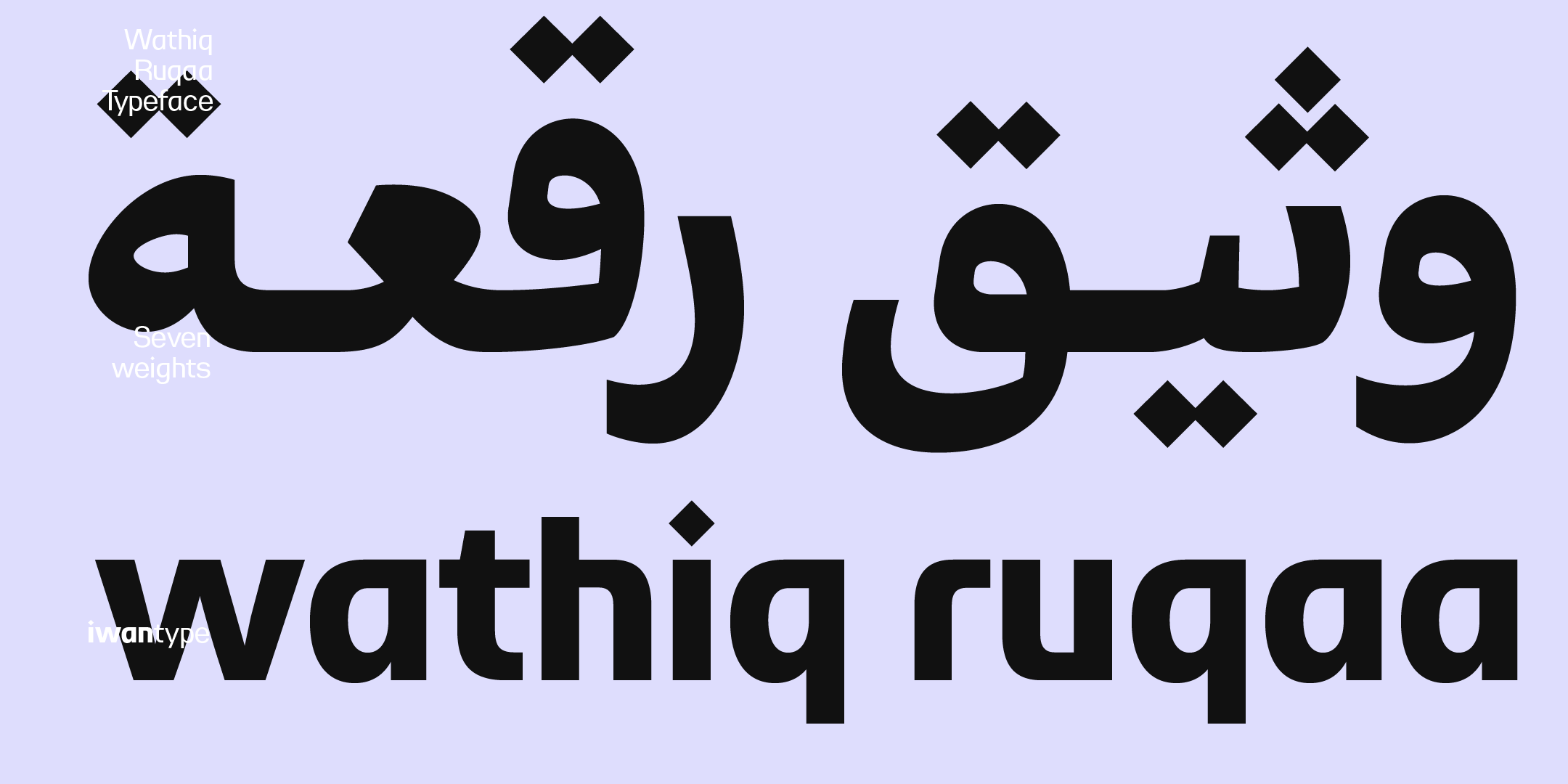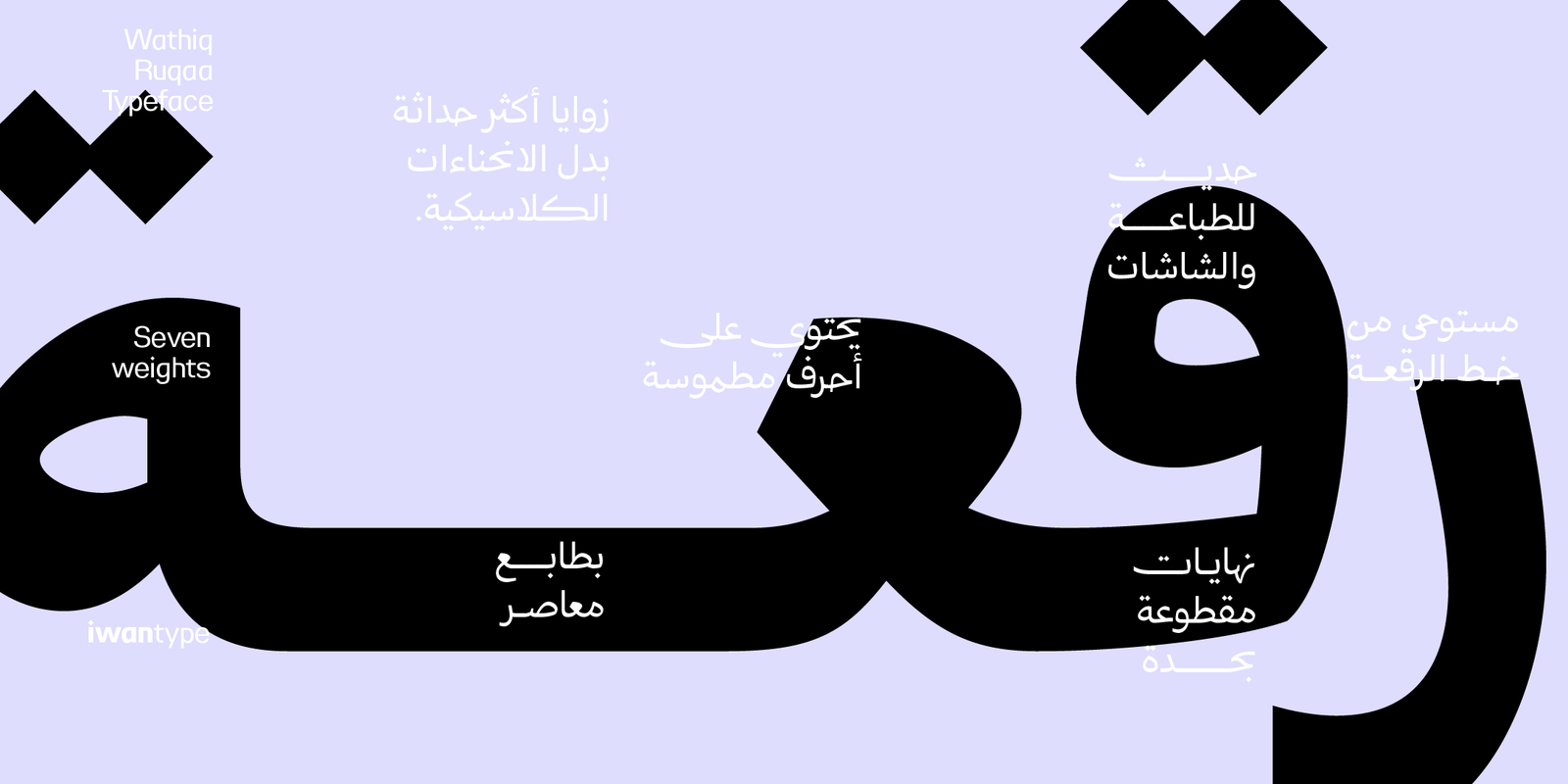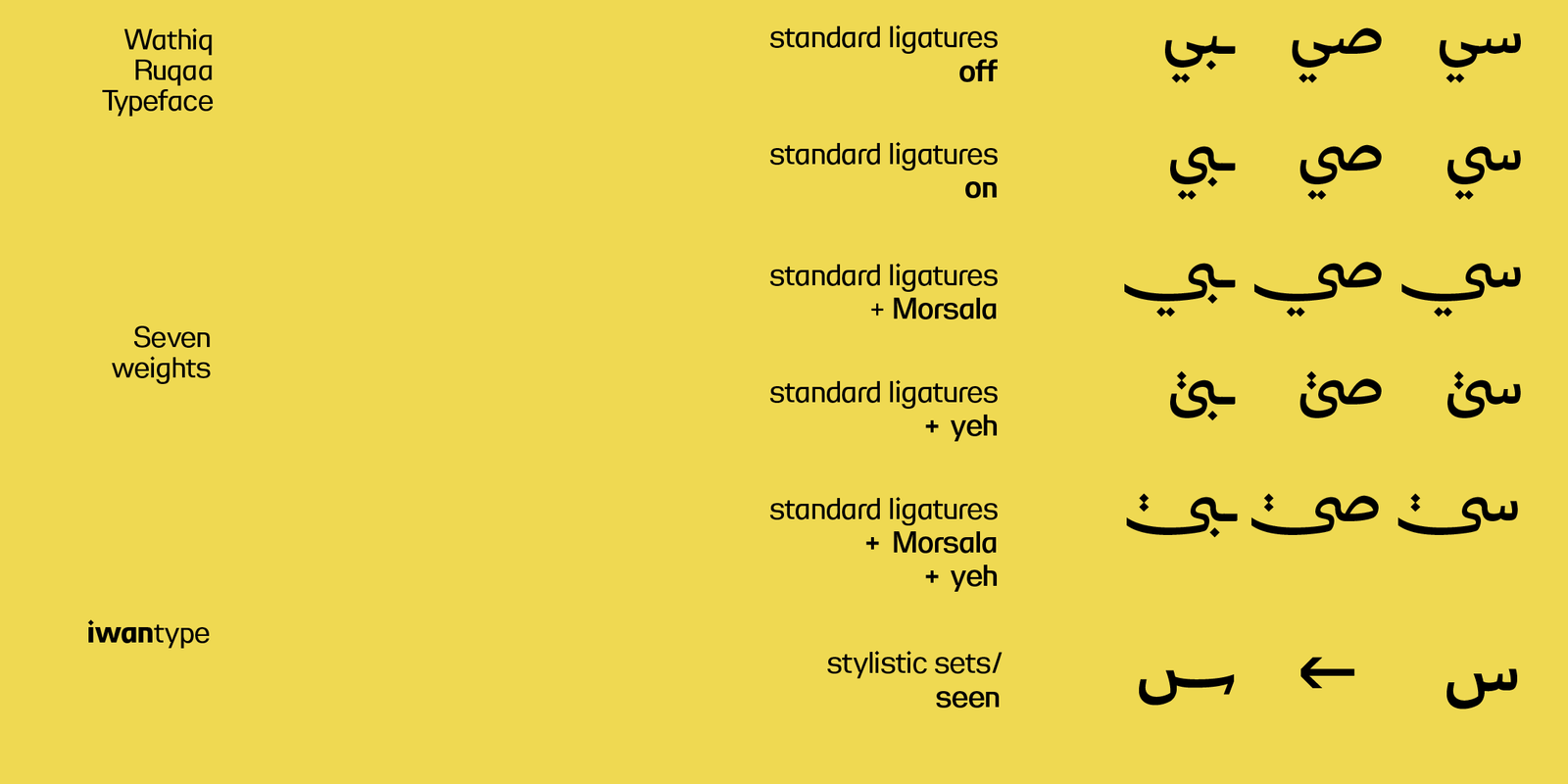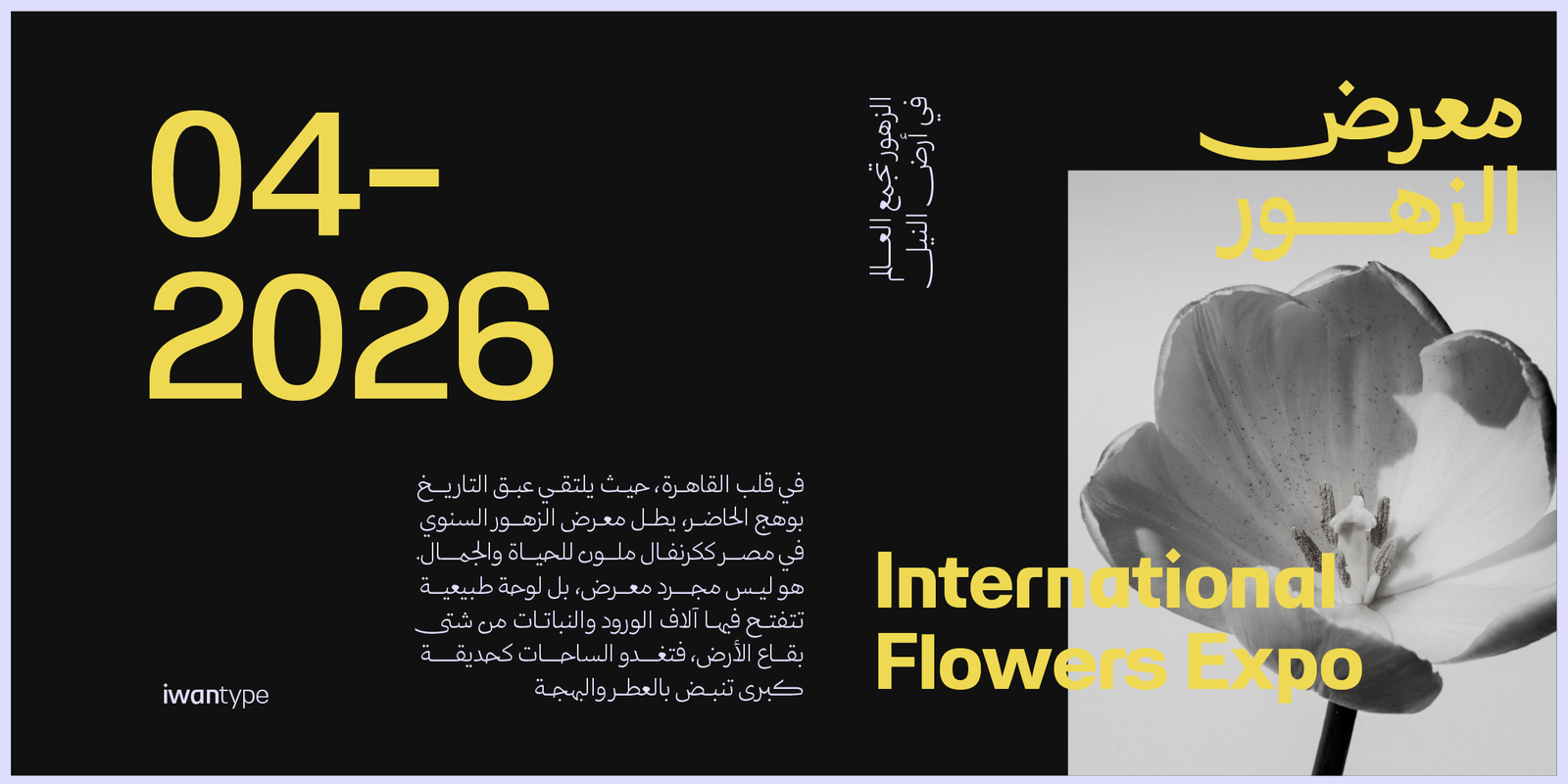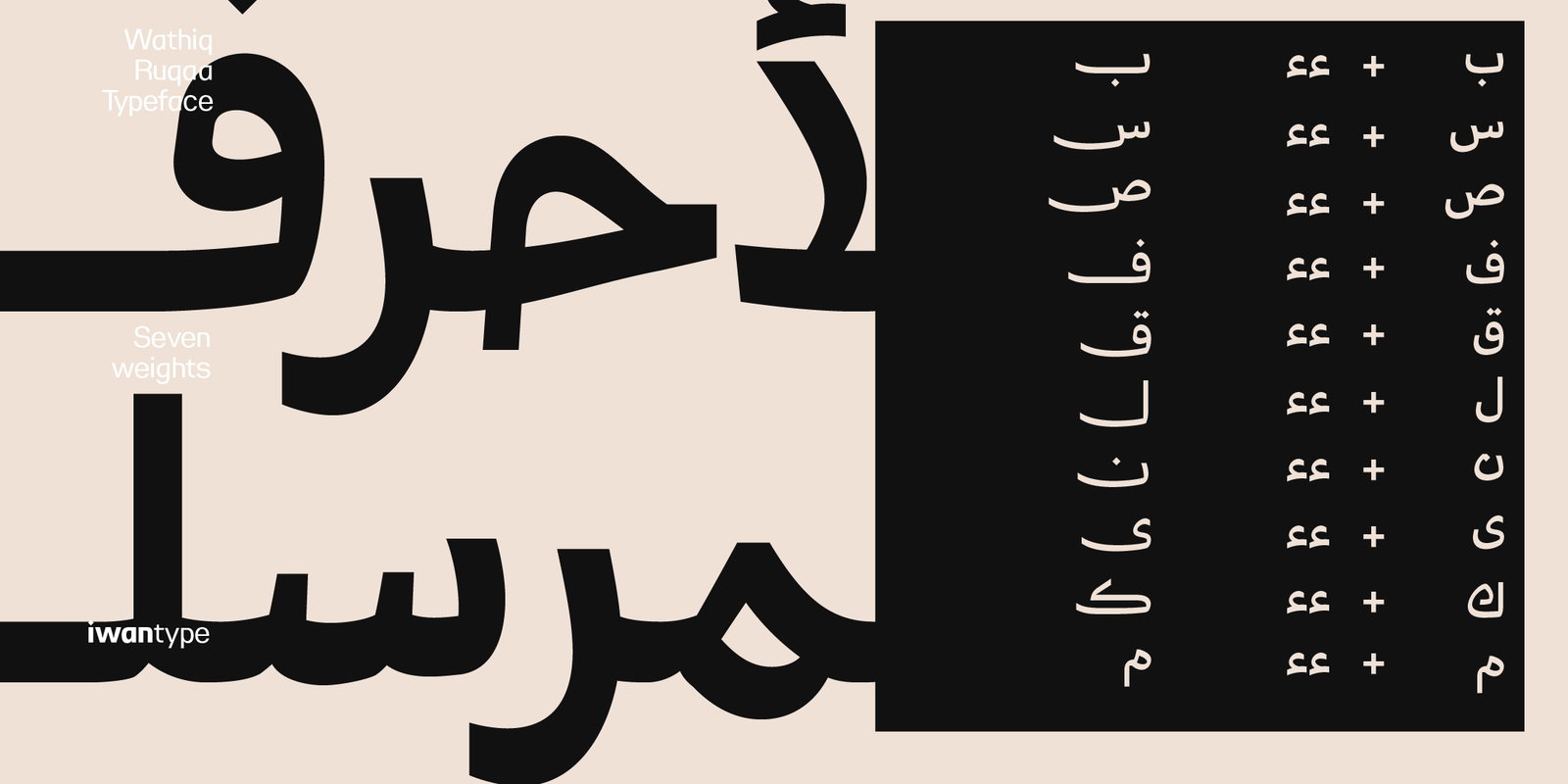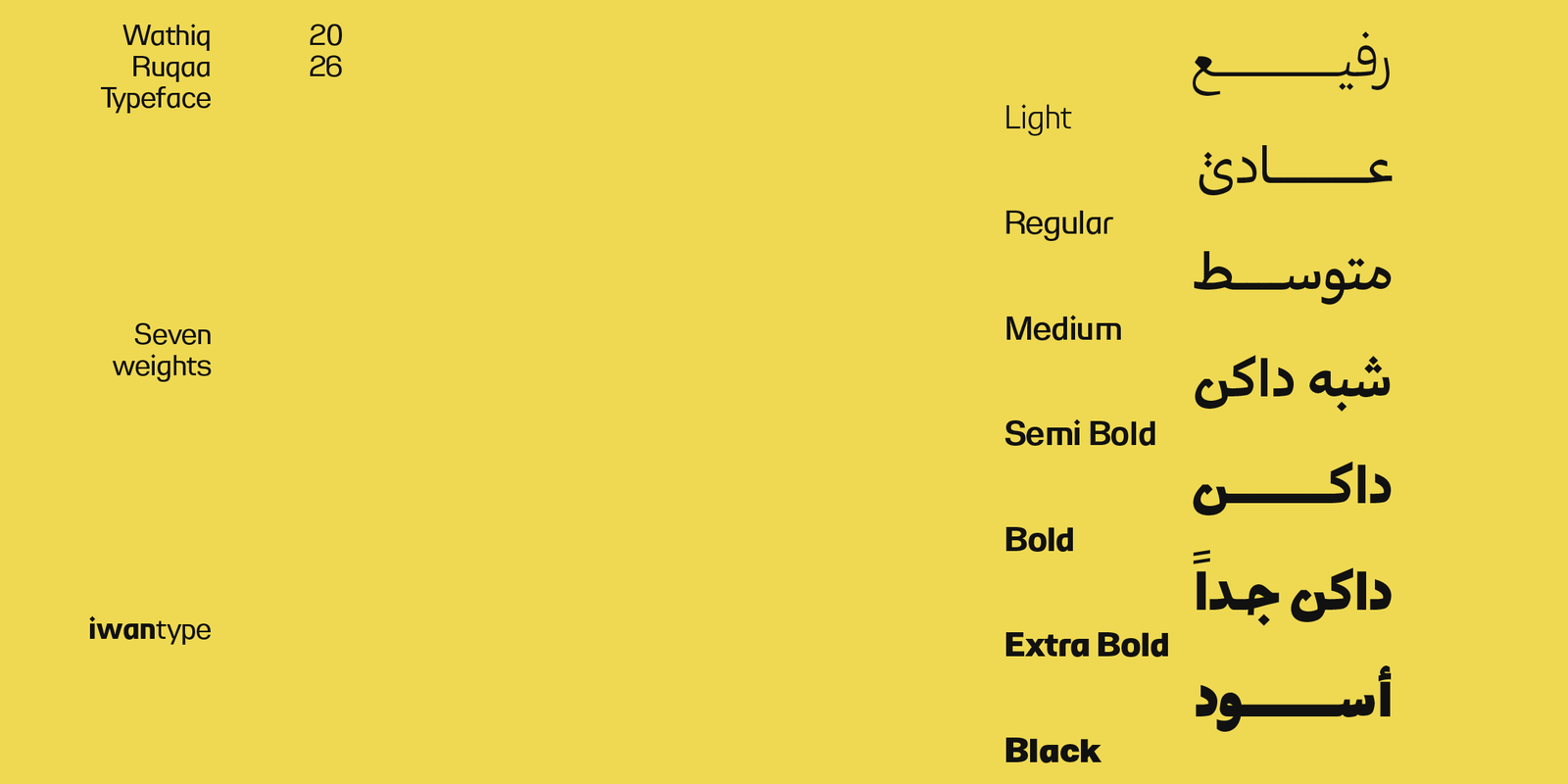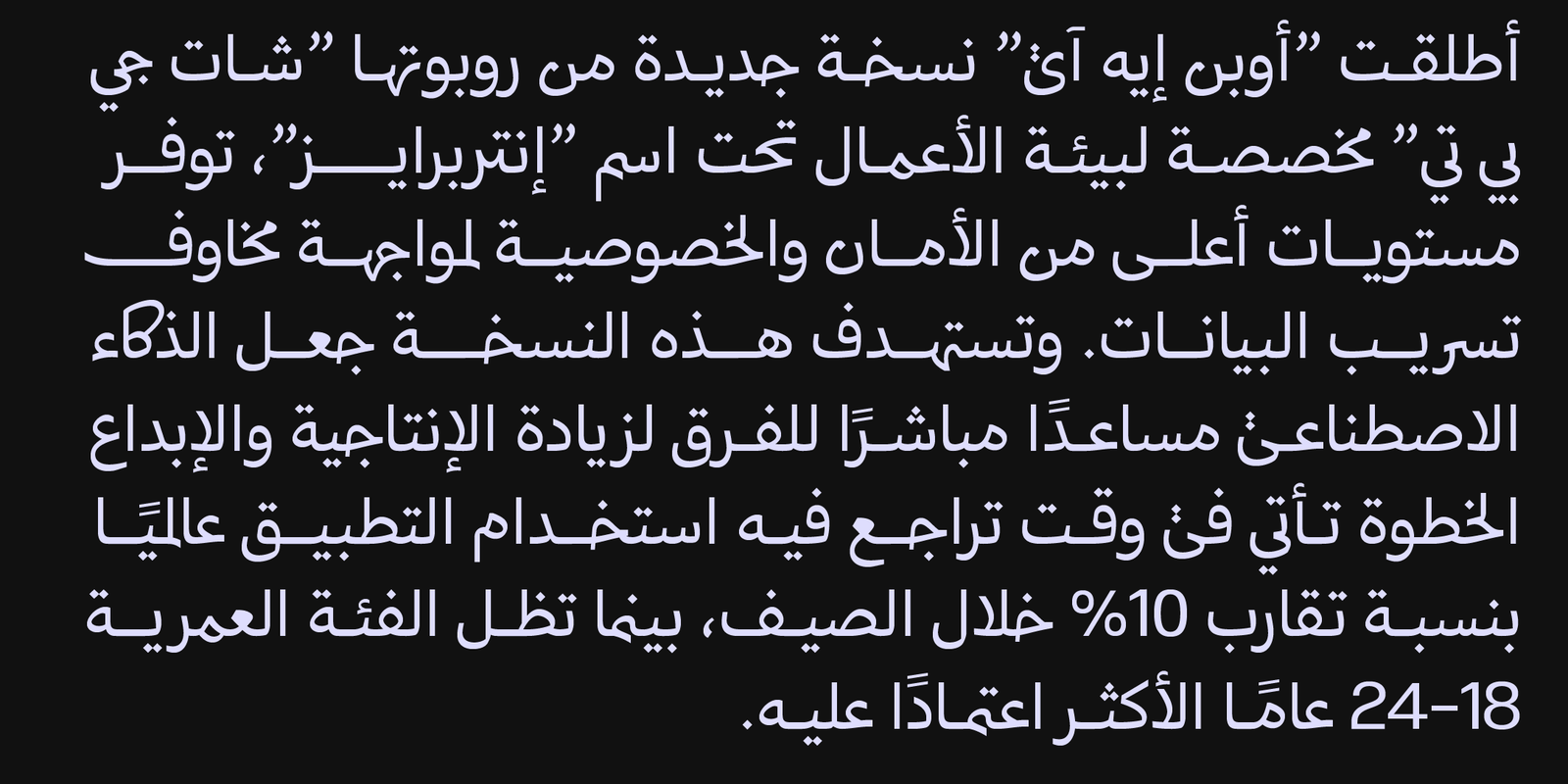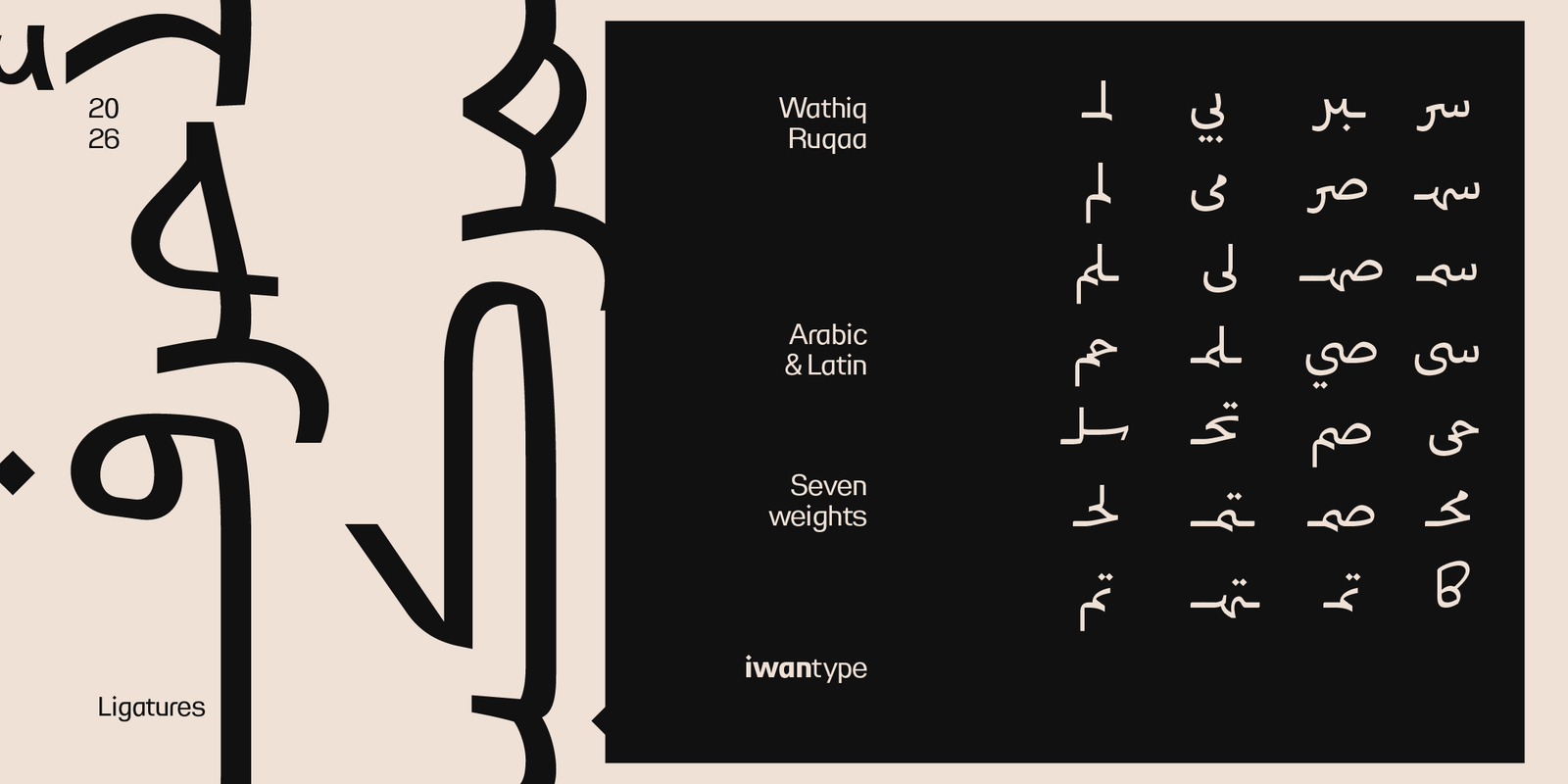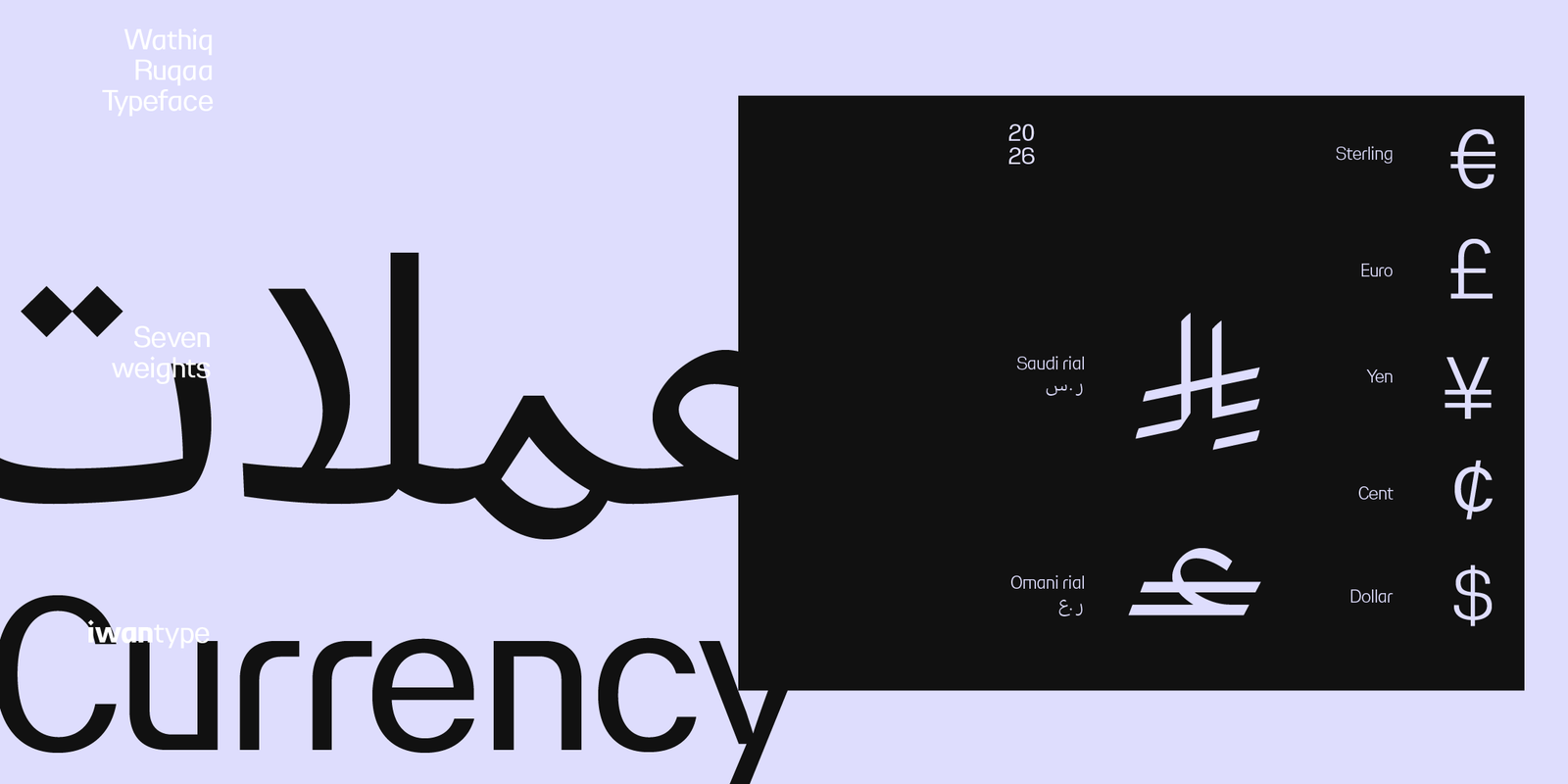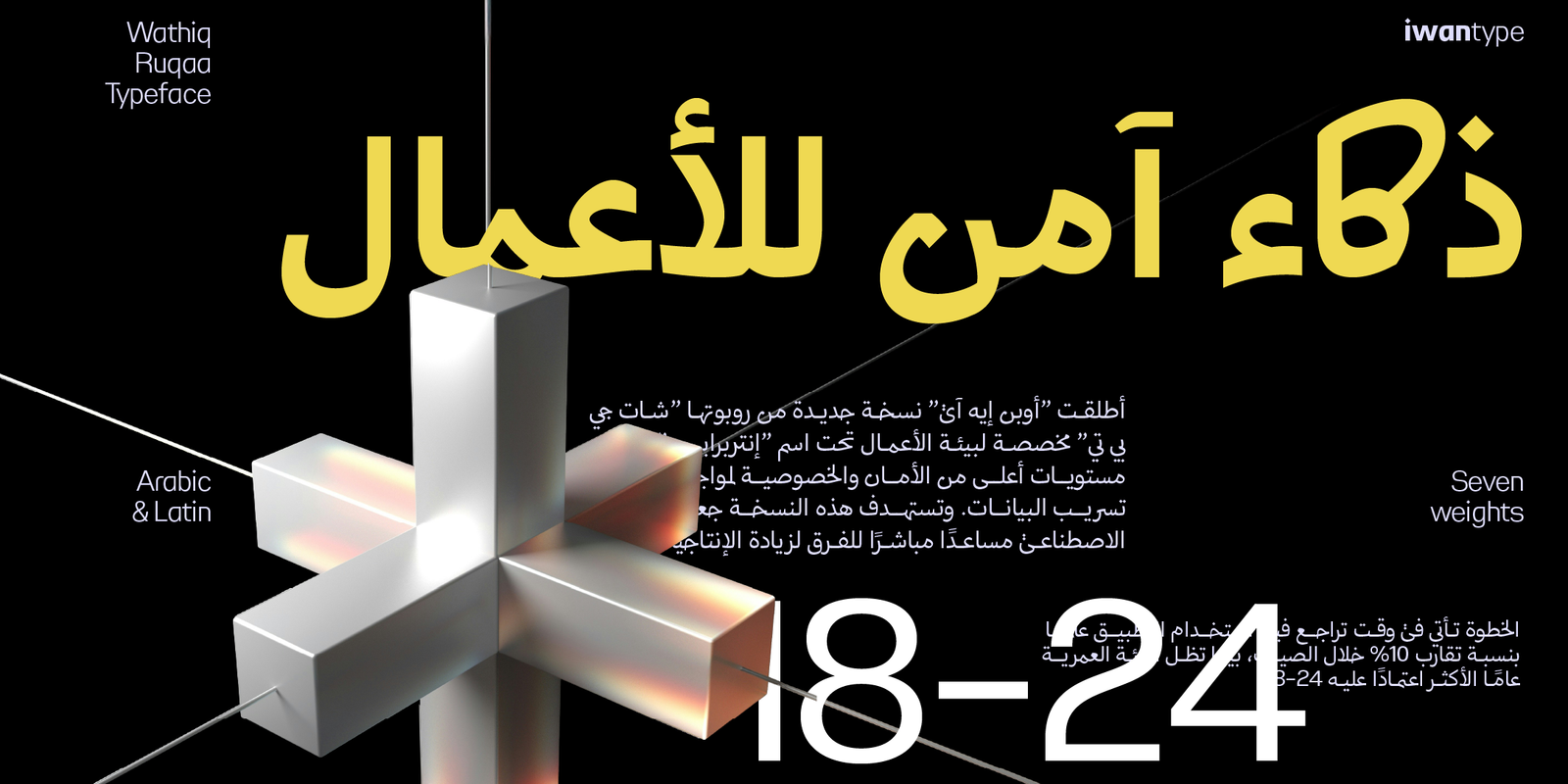
وثيق رقعة – Wathiq Ruqaa Typeface
وثيق رقعة هو إصدار حديث من عائلة خط وثيق الطباعية، مستلهم من روح خط الرقعة العربي، ومُعاد تصميمه بأسلوب معاصر يناسب الاستخدامات الطباعية الحديثة والواجهات الرقمية.
تم تطوير الخط ليجمع بين وضوح الرقعة التقليدي وسلاسة القراءة، مع بناء هندسي متوازن يمنح الحروف قوة بصرية وحضورًا واضحًا في العناوين والنصوص القصيرة.
مميزات خط وثيق:
يتضمن الخط العديد من مزايا OpenType التي تضفي عليه مرونة وتنوعًا في الاستخدام، مثل:
- أحرف مرسلة (تُفعَّل بإضافة “ءء” بعد الحرف)
- حرف ياء بنزول أقل: يقلل من نزول السطر، مما يعزز من انتظام النصوص.
- أحرف المركبة: تسهم في تحسين المظهر العام للنص وتزيد من سلاسته.
- نقاط بديلة
- يدعم رمز الريال السعودي والعماني، ويمكن تفعيله بإضافة حرف “ء” بعد كتابة كلمة “ريال”.